「美」のきれいな書き方
解説していきます(`・ω・´)ゞ
「美」の見本
こんな感じですね、美。
「美」の重要ポイント
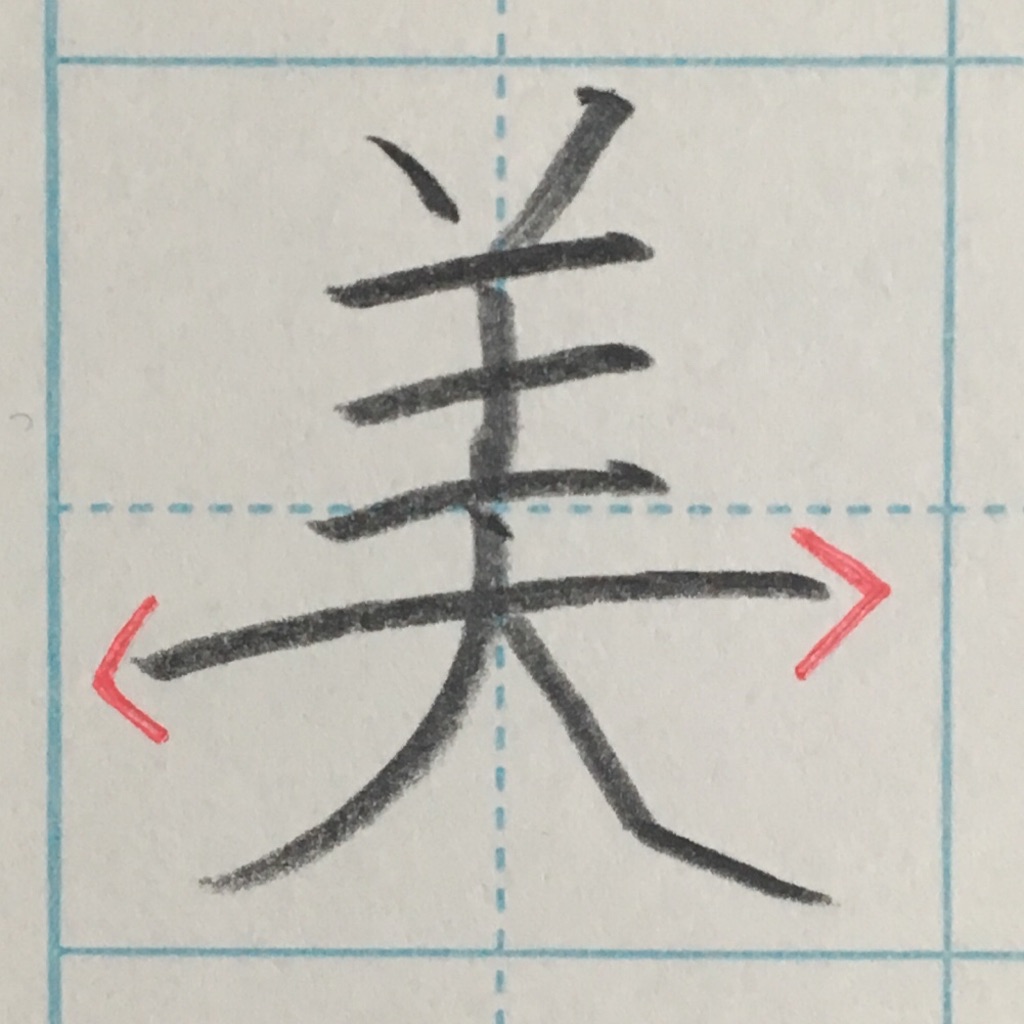
まずはこの横画!
一本、長く、強調しましょう。
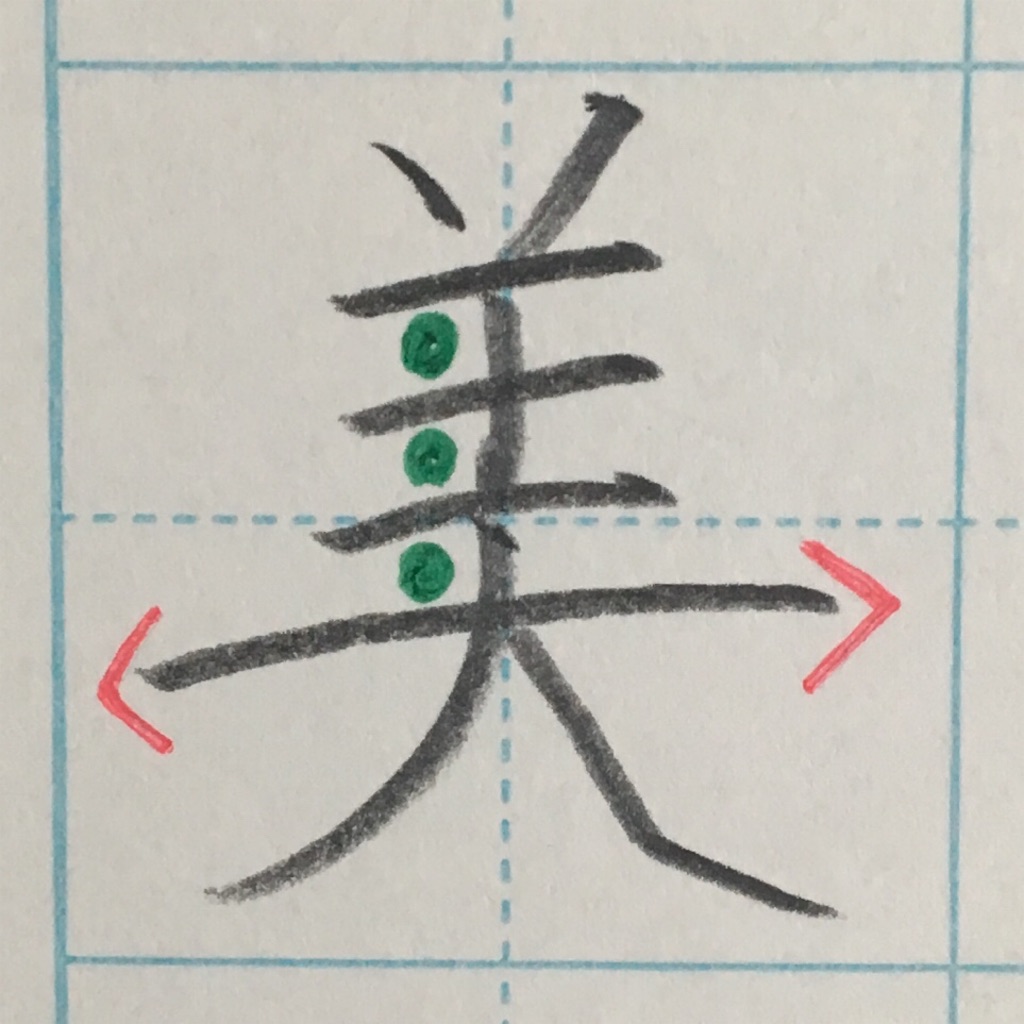
続いて、横画の間隔。
均等に揃えましょう。
「美」の細かいポイント
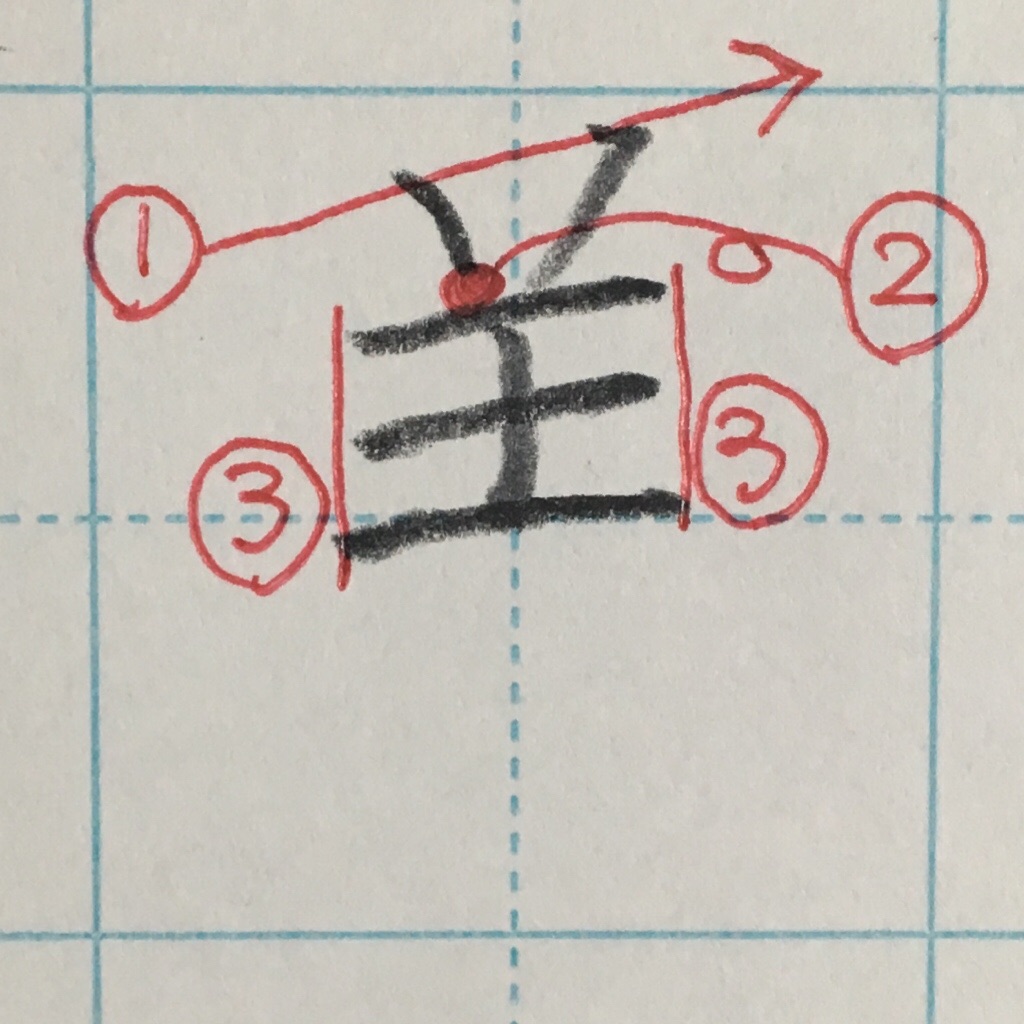
①2画目は少し高く。
②1画目は下にくっつかない。
③3本の横画は短く、同じ長さ。
(長さの目安は長い横画の半分くらい)
+α ここまでで、全体の上半分くらいに収めると◎
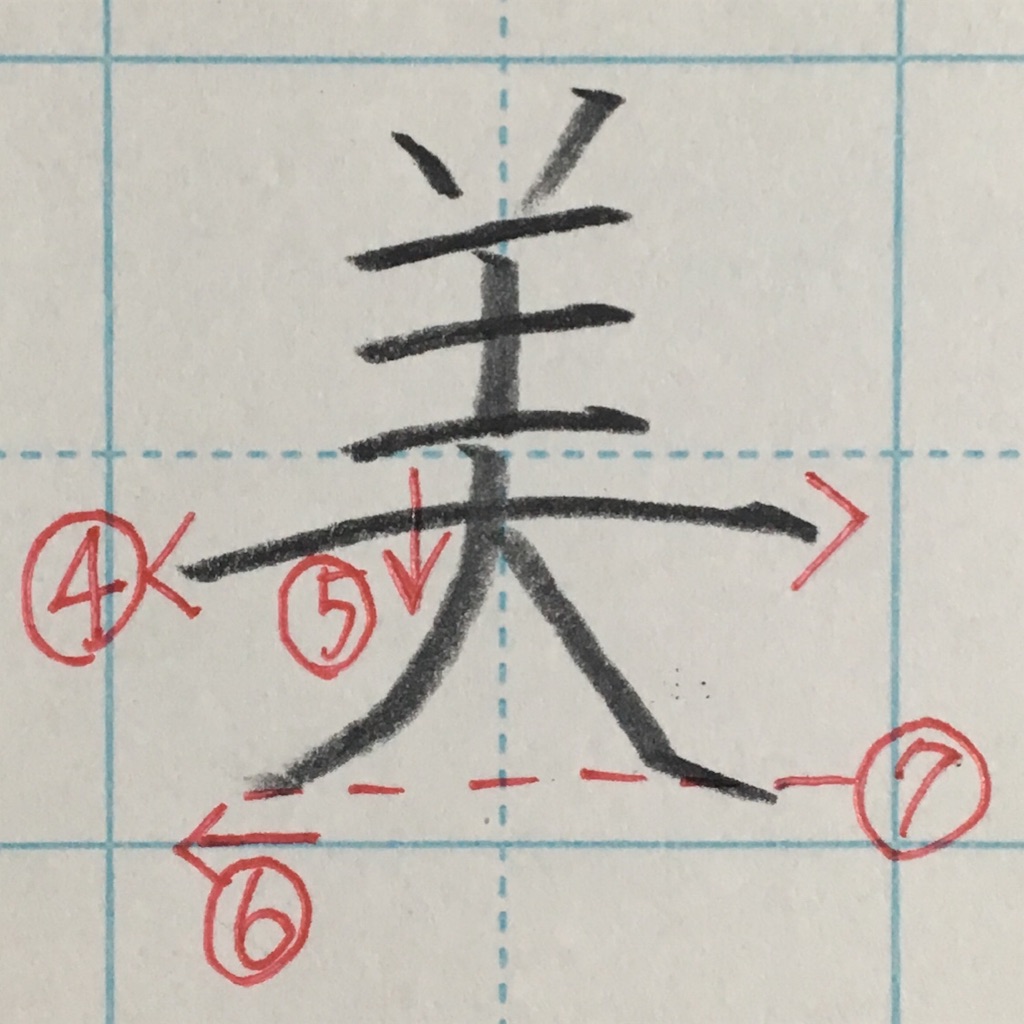
④ゆったりと、少し反ると◎
⑤8画目は、はじめはまっすぐに。
⑥最後は横向きに払う。
⑦下は大体揃える。
+α ④を強調するために、左右の払いはギリギリ④から出ない所までに。
【基本のき!】
☆横画は、ゆったりとした右上がりに。
☆右払いは、一度止めて、払う。
以上が「美」の書き方です。